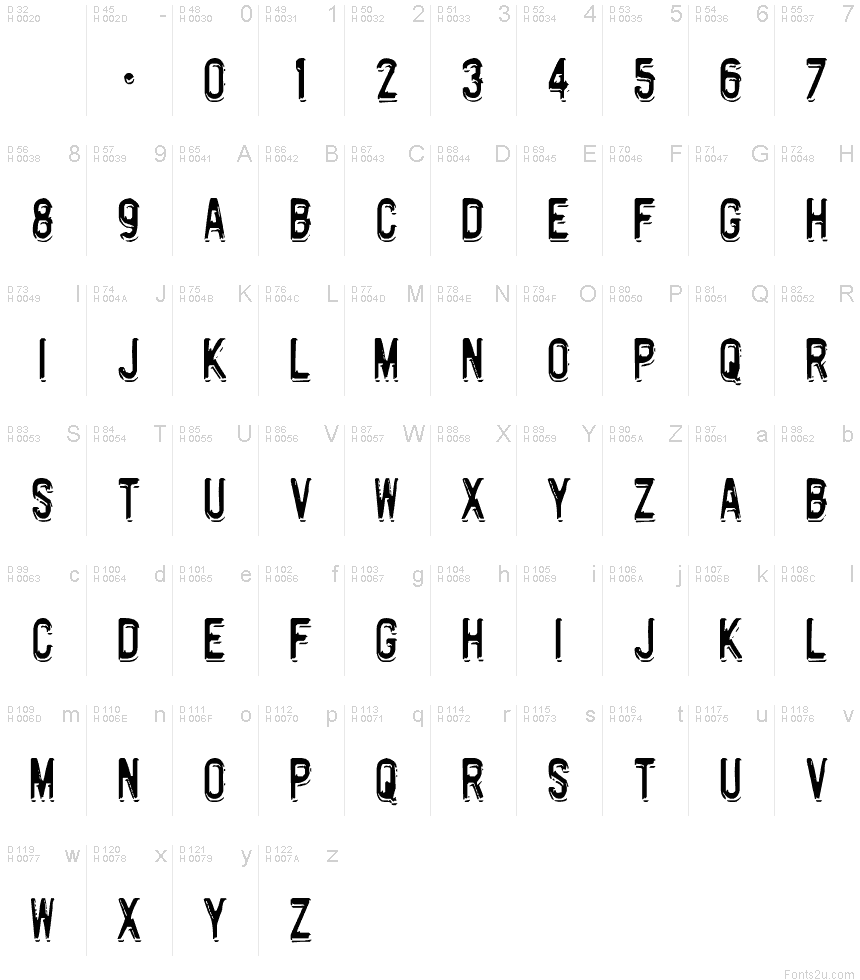
Motorway by Vic Fieger to darmowy, retro font typu display, inspirowany wysokimi drewnianymi literami, z wąską linią wewnętrzną, która tworzy efekt ramy, typowy dla dawnych plakatów. Nieregularne pęknięcia wzdłuż krawędzi wyglądają, jakby były wycięte bezpośrednio w projekcie, a nie dodane później, co nadaje literom wygląd zużytego, ręcznie malowanego szyldu.
Takie połączenie świetnie sprawdza się na plakatach warsztatowych, ulotkach rockabilly, menu barowych, grafikach na etykietach i opakowaniach w stylu vintage, gdzie efekt postarzenia musi pozostać dekoracyjny, a nie chaotyczny. Krótkie nagłówki i logotypy zyskują najwięcej, ponieważ detal wewnątrz litery i wyszczerbione krawędzie nadają każdemu słowu wyrazisty, „opieczętowany” charakter.